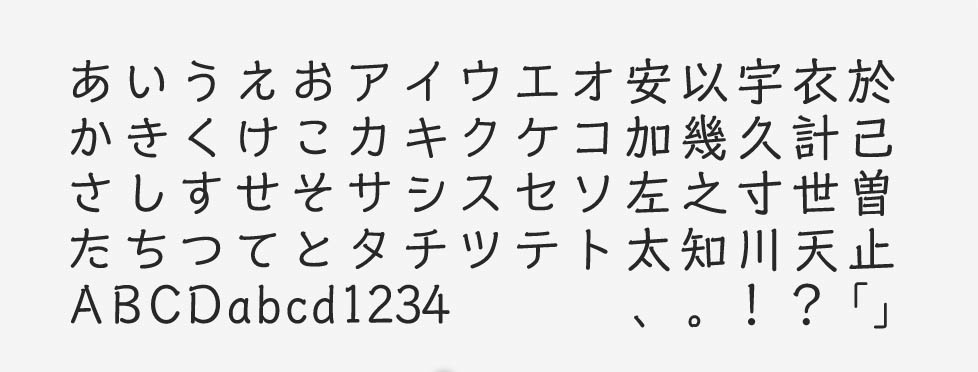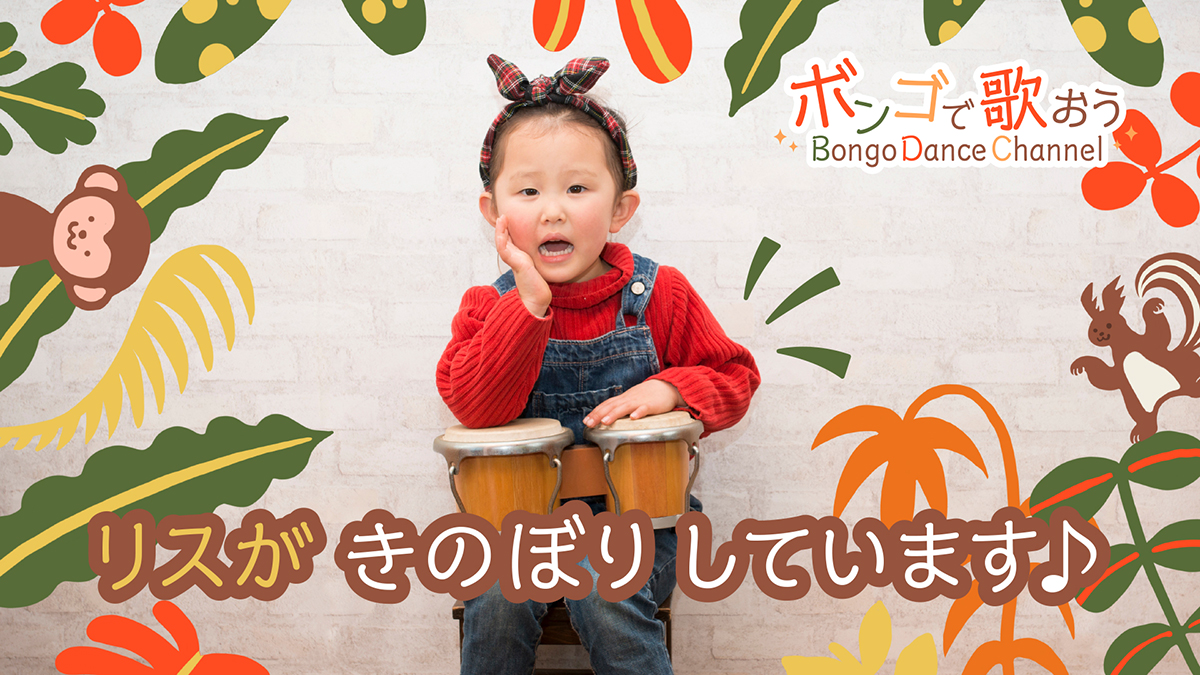
「トーキング」について
2014年にリリースされたトーキングは、素朴で優しいイメージの手書き風フォントです。映画の字幕の文字を、より自然な形に近づけた独特の表情を持つようなデザインに仕上げられています。懐がやや広く、ハライとトメが重なる部分をあえてくっ付けたり、随所に隙間を持たせたりするなど、たっぷり工夫が盛り込まれている書体です。
「トーキング」の特徴
トーキングは、同じくモリサワの映画字幕系の書体のシネマレターと比べると字面が小さく、可愛らしい印象を与えます。語りかけるような雰囲気で、TVや動画の字幕・テロップに最適であることはもちろん、絵本の本文などで使っても窮屈な読みにくさはありません。
広めに設計されたふところが穏やかな印象で、柔らかな内容を伝える場面に適しています。直接的に映画に関連した制作物や、映画のような演出で見せたいデザインにも幅広く活用できるフォントです。
作例でのテキストはMVの前面に乗せるテロップなので、フチ文字で扱って視認性を高めました。色使いで楽しそうな雰囲気を強調し、可愛いイラストも組み合わせることで、子どもたちに興味を持ってもらいやすいようにデザインしています。
本文、雑誌、絵本、アニメ、パンフレット、チラシ、字幕テロップ、POP、スマートデバイスの画面